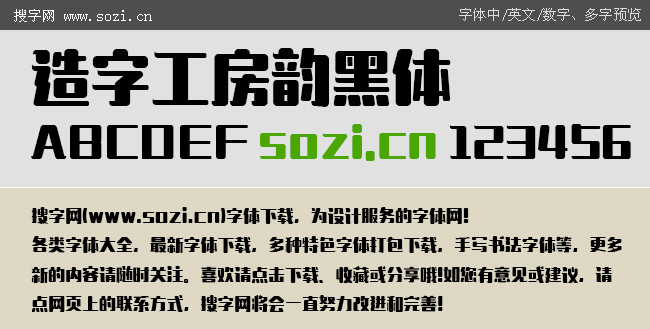
造字工房韻黑體
搜字網(wǎng)給大家提供一款造字工房韻黑體中文字體下載,造字工房韻黑字體結(jié)體方正均衡,字形飽滿沉穩(wěn)有力,在筆畫轉(zhuǎn)折間巧用圓角,令其更顯圓潤。橫畫上以蠶頭起筆,細(xì)膩出彩,剛健質(zhì)樸卻又不失靈動(dòng)飄逸之感。適合應(yīng)用于書籍裝幀設(shè)計(jì)、包裝設(shè)計(jì)、海報(bào)設(shè)計(jì)、網(wǎng)頁設(shè)計(jì)等應(yīng)用。(本字體為個(gè)人非商用版,如需要商用請(qǐng)聯(lián)系官方購買版權(quán))